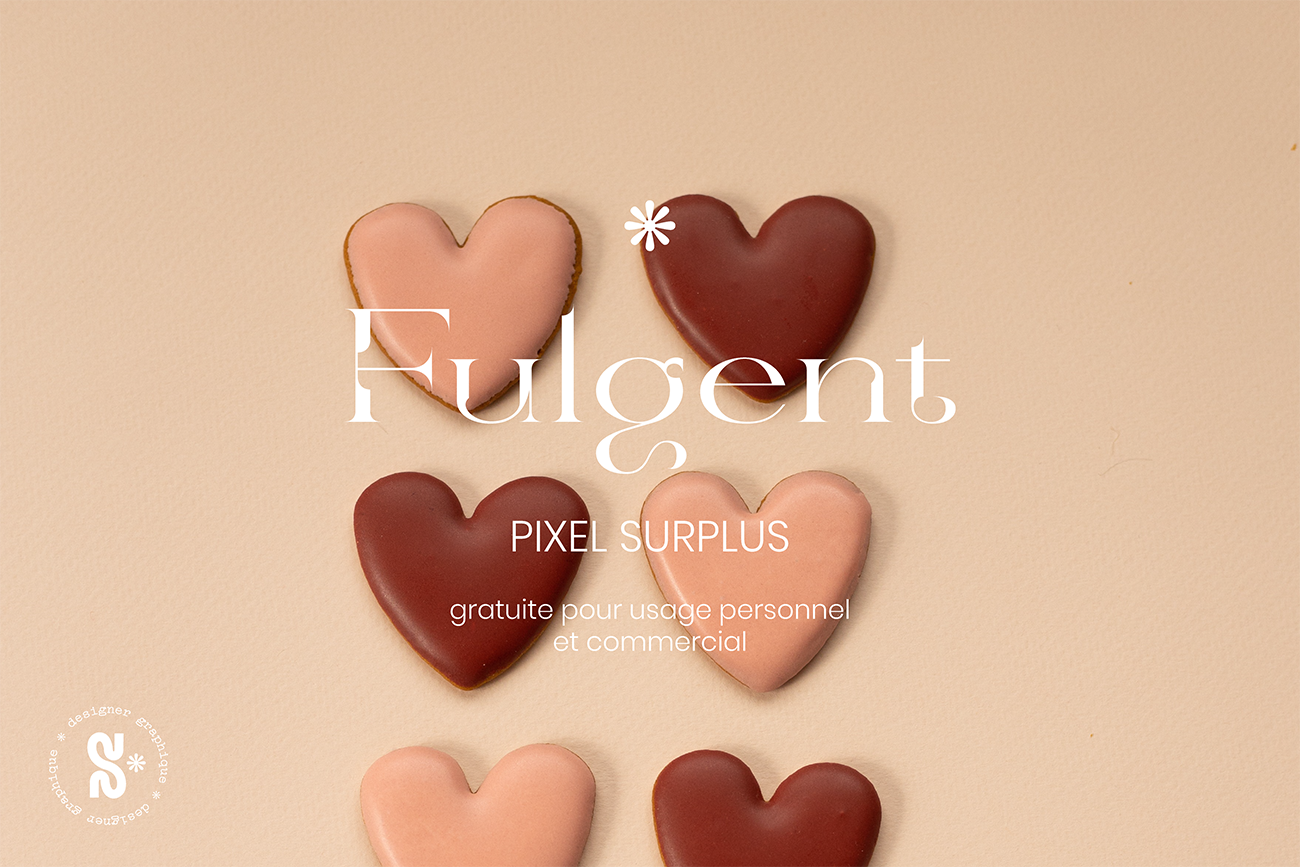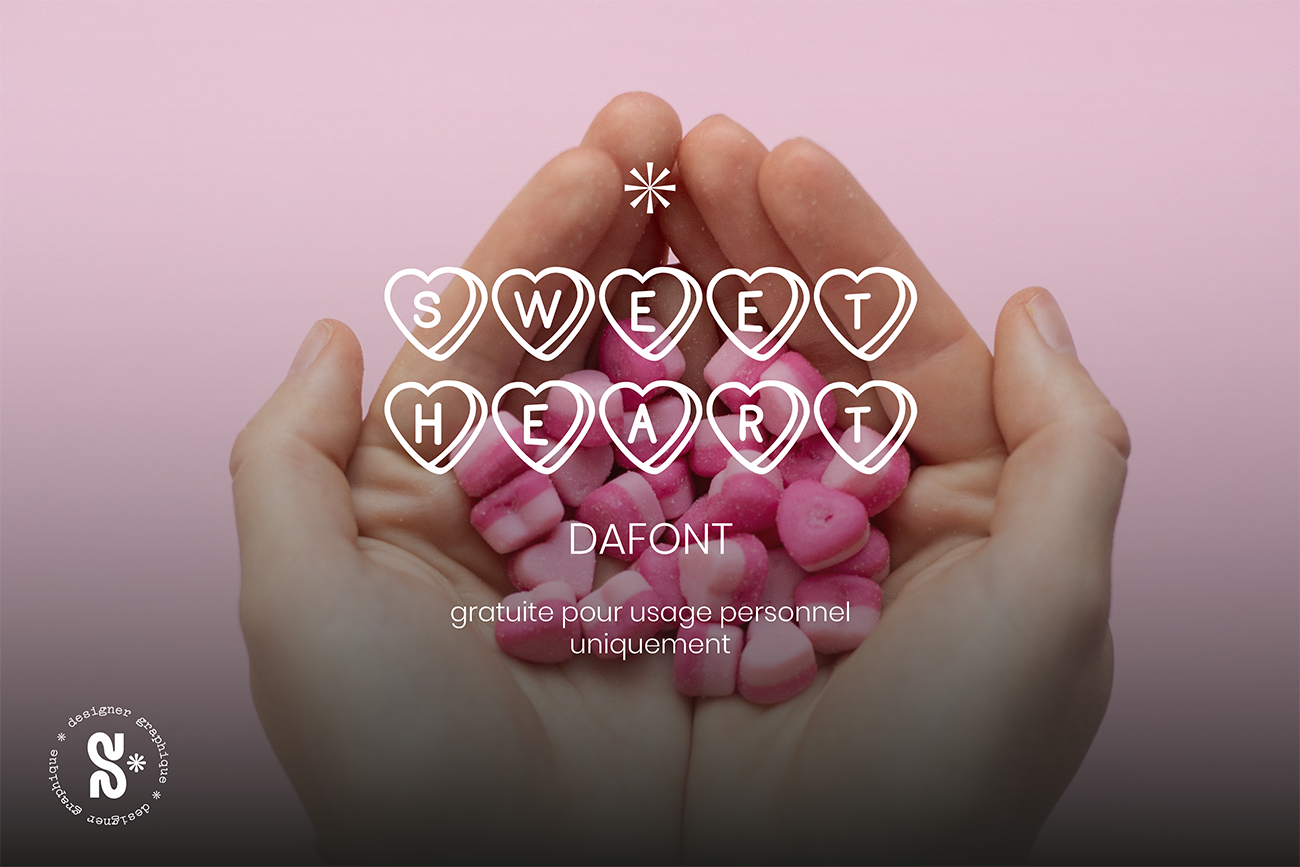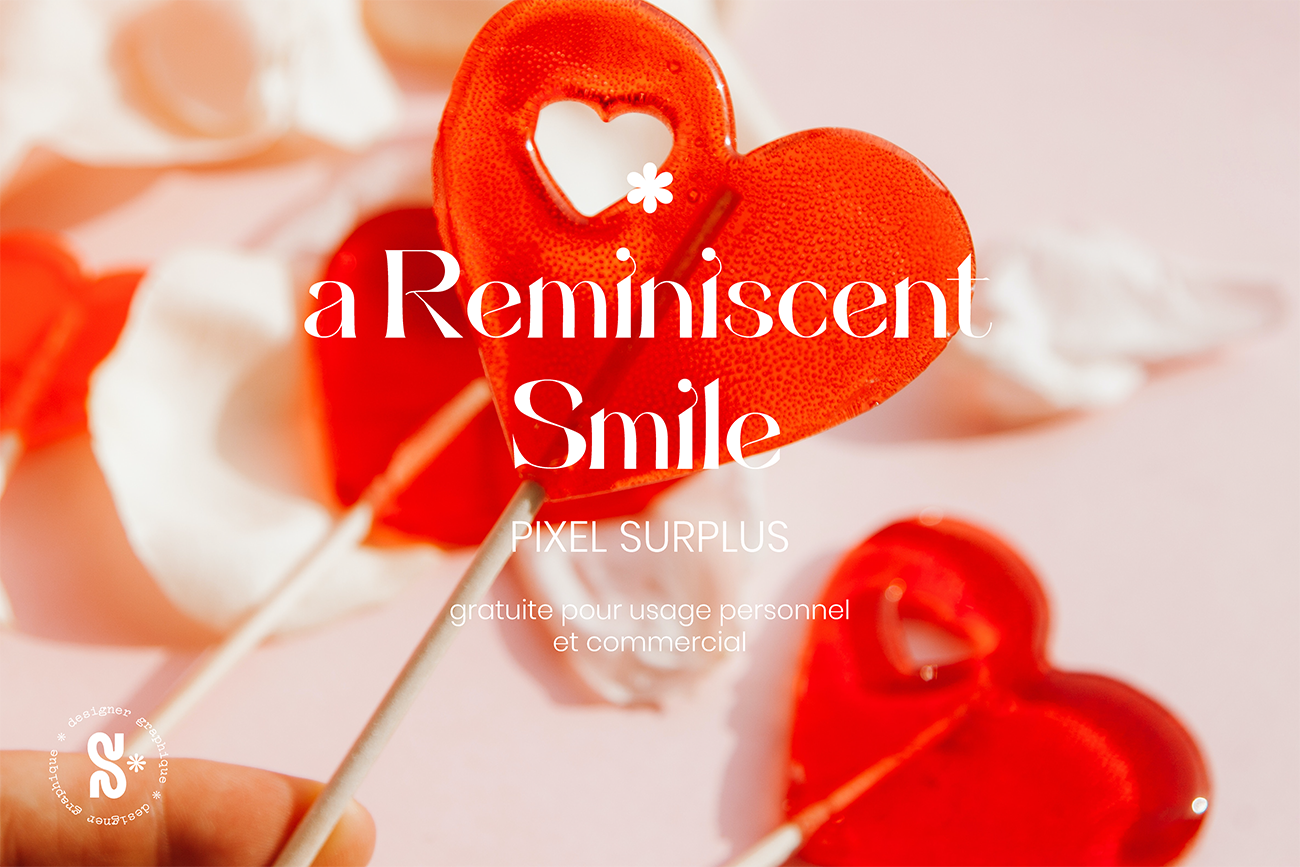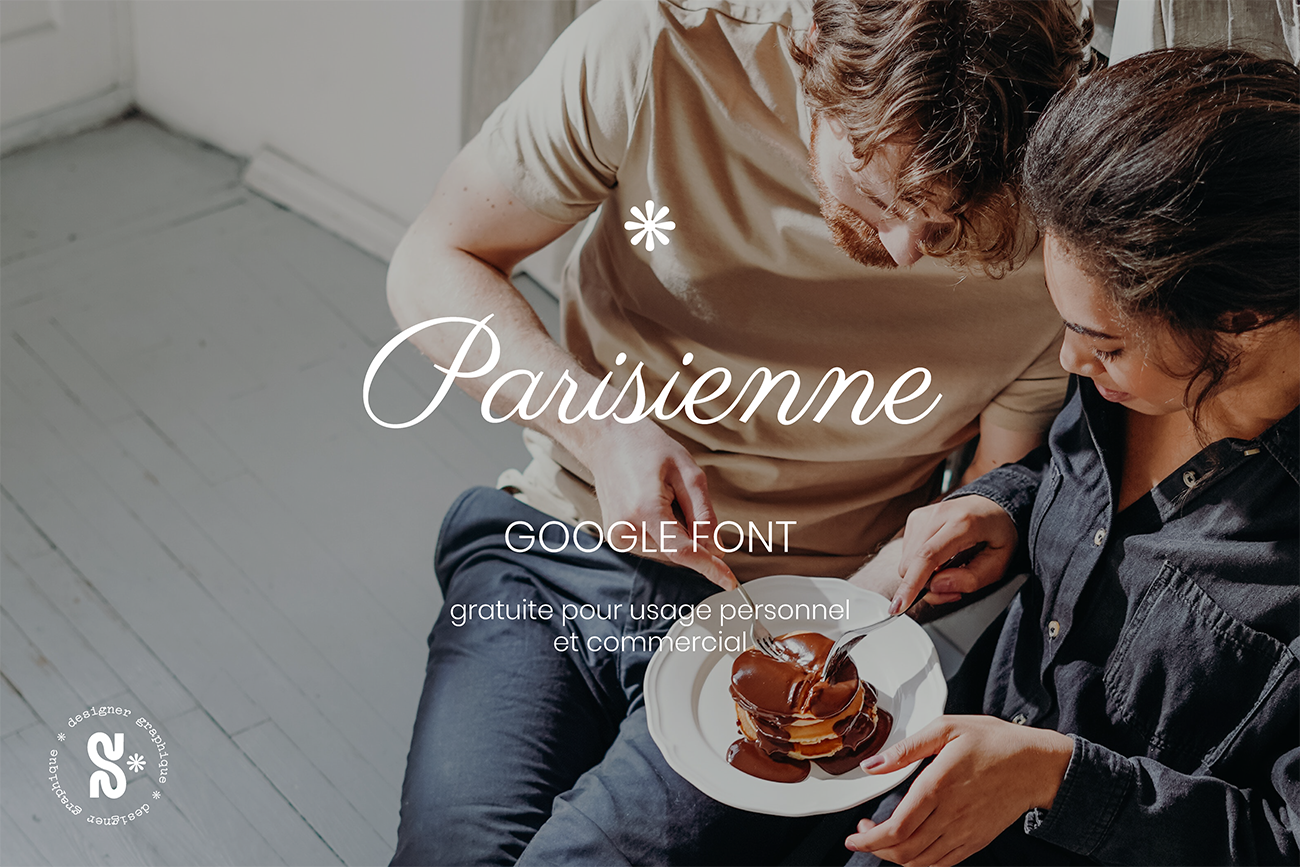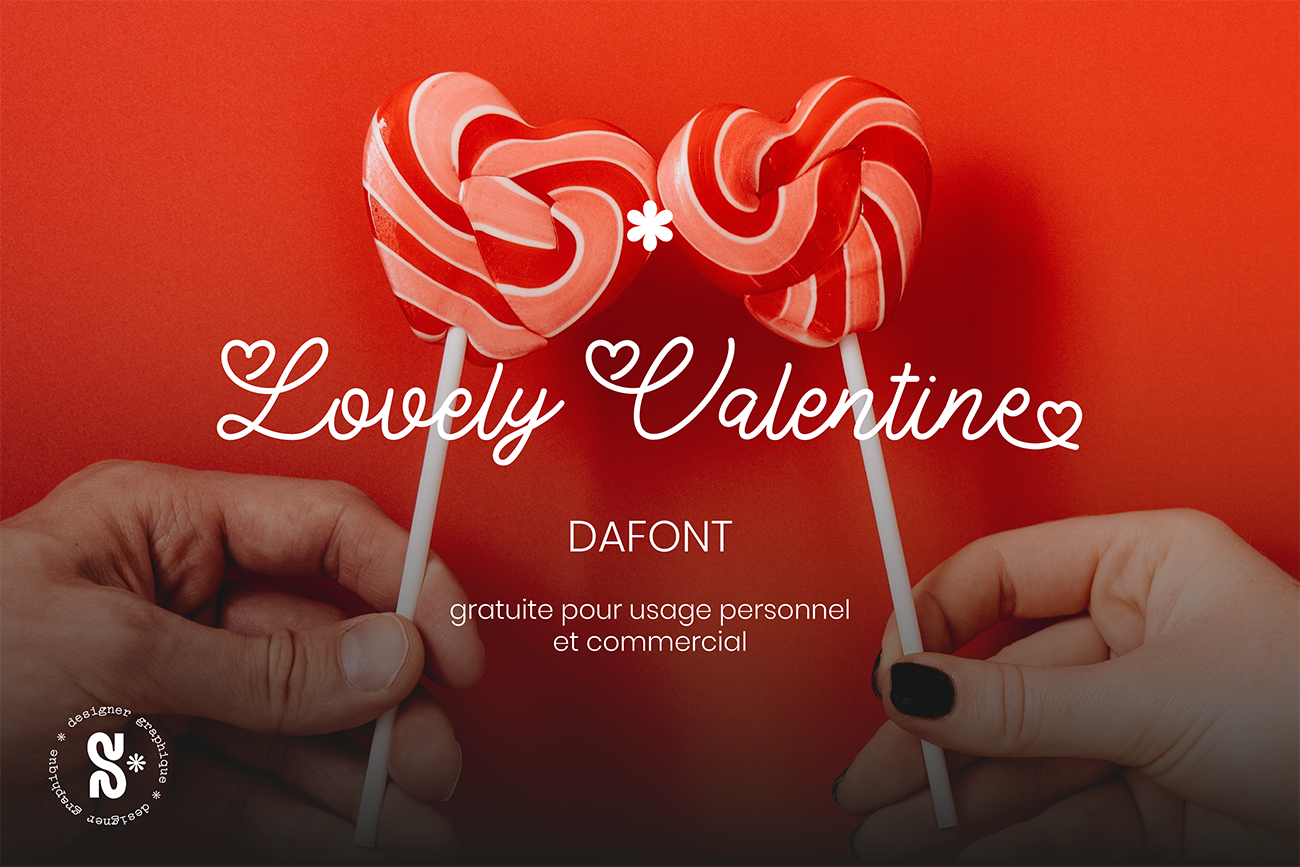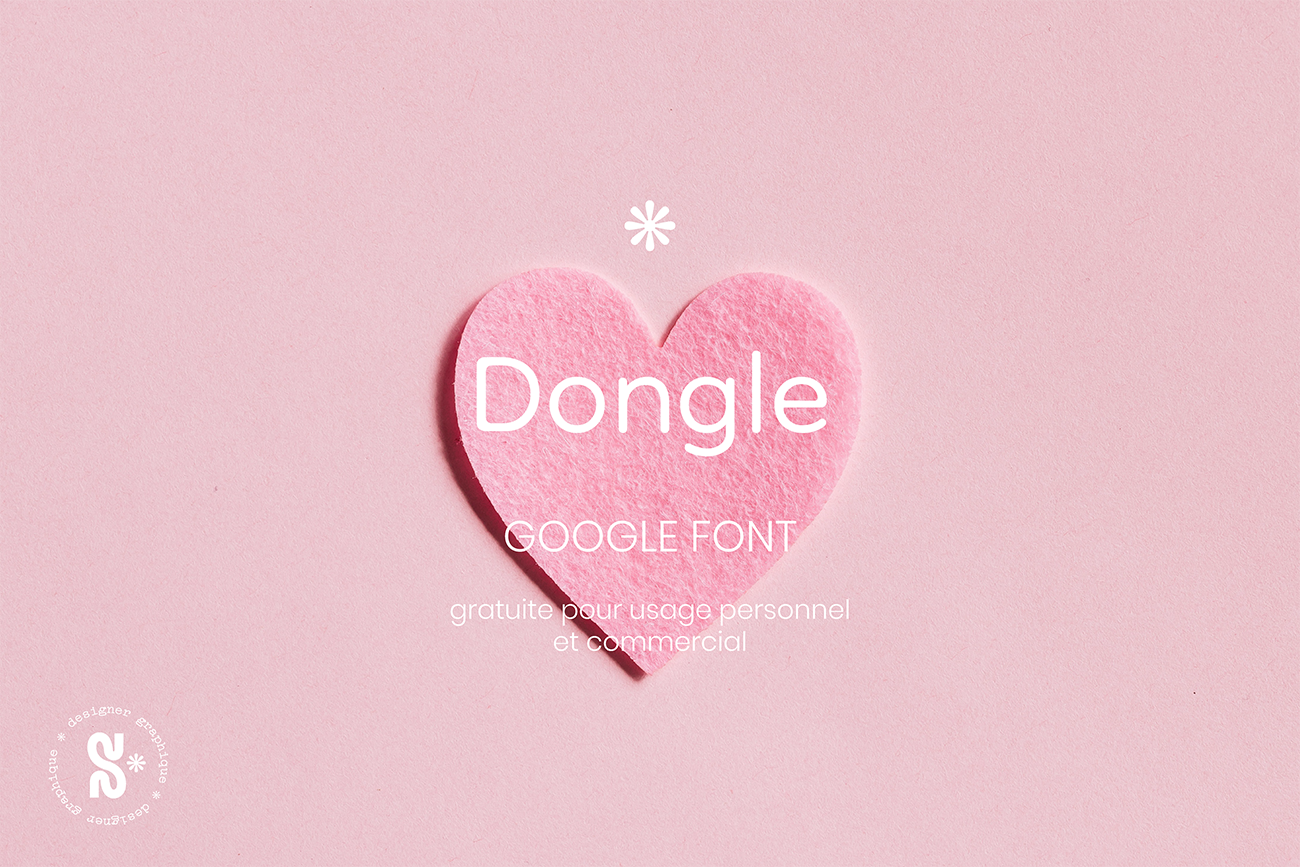
Cela n’a pas du vous échapper, la Saint Valentin approche et la communication s’adapte en conséquence ! Mais qu’en est-il de votre propre communication à cette période ? Pas facile de se démarquer parmi toutes les publications sur notre ami Valentin. Dans ce studio de graphisme, on adore communiquer sur toutes ces fêtes qui ponctuent l’année ! Je me suis dit que c’était le moment de vous aider à communiquer grâce à une sélection de 10 typographies du love gratuites ! Mais avant ça, faisons le point sur la communication pendant la Saint Valentin.
Une communication de Saint Valentin pour célébrer l’amour
Vous souhaitez surfer sur la vague et en profitez pour avoir de nouveaux contenus à poster ? Je vous en dit un peu plus sur cette fête de l’amour et sur ce que vous pourriez mettre en place pour cette occasion.
La Saint-Valentin : une histoire d’amour (ou presque)
Si pour beaucoup la St -Valentin est une fête commerciale, c’est avant tout une journée censée célébrer l’amour. Son histoire remonte au XIVème siècle et est légèrement plus triviale; direction la Grande-Bretagne. À l’époque, on pensait que les oiseaux choisissaient ce jour pour s’apparier, on a donc décrété que le 14 février serait la fête de l’amour. Avec le temps, les amoureux ont pris pour coutumes de s’échanger des billets doux, des fleurs ou encore des chocolats.
Aujourd’hui, impossible de passer à côté de cette fête annuelle. Elle est omniprésente, et si vous souhaitez communiquer sur le sujet, il est important de vous démarquer ! Publications sur les réseaux sociaux, vidéos, petits mots (en tout bien tout honneur) à vos clients…
Autant de supports qui peuvent vous permettre de vous différencier facilement si vous avez les bons outils. Alors pour lâcher un peu la pression, suivez mes conseils de designer graphique !
Comment communiquer à la Saint Valentin
Alors comment communiquer et surtout QUE communiquer pour la Saint Valentin. Selon votre marque, la communication de St Valentin aura plus ou moins d’importance. Si votre produit est étroitement lié à cette fête (bijoux, fleurs, chocolats, papeterie…) il est important de vous différencier. Mettez en avant l’amour sous une autre facette. Communiquez sur vos événements, vos offres spéciales, etc.
À la Saint Valentin comme à tout autre moment de l’année, il est appréciable de se différencier. Vous pouvez par exemple faire une série de posts avec des couleurs liées à cette fête : le rose, le rouge… tout en gardant les éléments phares de votre charte graphique : typographies, éléments graphiques, etc. À l’inverse, vous pouvez conserver vos couleurs mais utiliser une typographie à part entière pour parler d’amour à vos clients (car ce sont eux votre plus belle histoire d’amour, pas vrai ?).
Et si je ne changeais rien pour ma communication de St-Valentin
Mon conseil le plus important ? Lâcher prise. Vous ne souhaitez pas communiquer différemment lors de la Saint Valentin ? Vous pensez que cela n’est pas pertinent auprès de votre cible ? Alors ne changez rien ! Il est important de ne pas céder à la pression du moment et de s’écouter.
Les fêtes sont une belle occasion de communiquer certes, mais il est important de le faire de la bonne manière et en accord avec les valeurs et envies de votre projet. Comme je le dis souvent; la qualité avant la quantité.
Mon cadeau de Saint Valentin
En cette période où l’on s’échange des mots doux, je vous partage 10 typographies parfaites pour votre communication de Saint Valentin. Entre tradition et audace, ces polices donneront à vos créations une touche unique afin de vous démarquer. Et petit plus : elles sont gratuites !
Prêtes et prêts à découvrir cette sélection ? Ouvrez grand votre coeur et laissez-vous guider !
1 – Une communication de Saint Valentin unique avec Fulgent
Fulgent est une typographie gratuite parfaite pour une communication de Saint Valentin différenciante. Originale par ses lettres aux futs coupés, elle apporte un côté rêveur pour une communication délicate. À découvrir sur Pixel Surplus
2 – Le fun de la typographie Sweet Heart
Sweet Heart est la typographie de Saint Valentin version US par excellence : fun et gourmande. Elle est inspirée de le marque de bonbon américains du même nom en forme de coeur. Un clin d’oeil que j’adore ! À télécharger gratuitement sur Dafont
3 – La délicatesse de la police A Reminiscent Smile
La typographie A Reminiscent Smile est délicate et offre quelques courbes évoquant la calligraphie. Une font qui donne un côté luxueux à votre communication de St-Valentin ! À retrouver gratuitement sur Pixel Surplus
4 – La typographie calligraphique chic : Parisienne
Si je ne suis pas une grande amoureuse des typographies scripts, je dois avouer que la font Parisienne me fait de l’oeil. Imitant une écriture calligraphique humble, elle est équilibrée et parfaite pour un côté « lettre à l’amour ». À découvrir sur Google Font
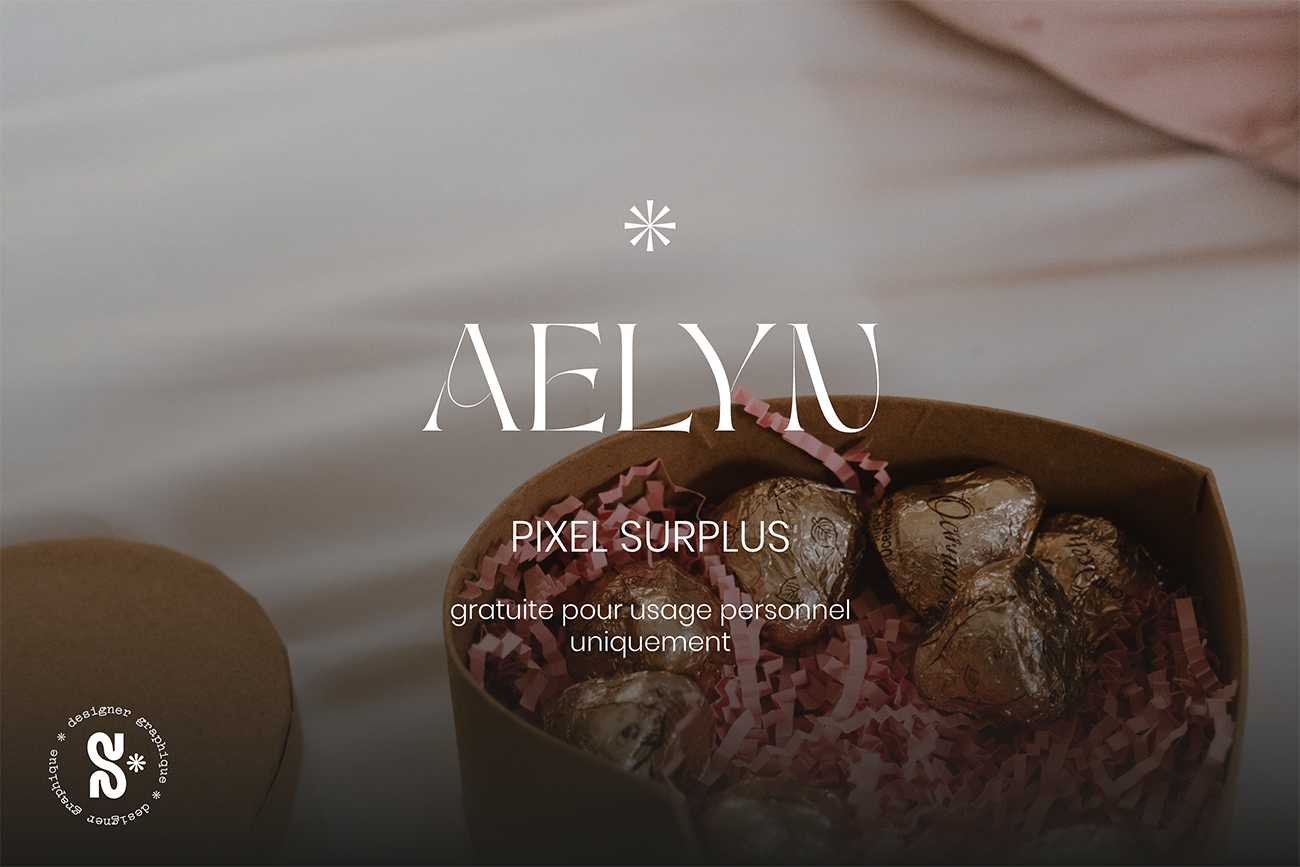
5 – L’équilibre entre élégance et modernité avec la police Aelyn
C’est un de mes coups de coeur de la sélection, la police Aelyn marie à merveille l’élégance d’une typographie Sérif tout en lui apportant des courbes rondes. Ses traverses atypiques en font selon moi une typographie différenciante et unique ! À télécharger gratuitement sur Pixel Surplus
6 – La typographie Lovely Valentine pour une communication 100% love
Lovely Valentine est une typographie faite pour la St Valentin. Ronde, douce et juste ce qu’il faut de variation pour la rendre dynamique. Les petits coeurs sont le plus 100% Saint Valentin. À retrouver gratuitement sur Dafont
7 – La rondeur pleine d’amour de Dongle
Vous souhaitez apporter une touche minimaliste à votre communication de St-Valentin ? Rien de mieux que d’utiliser la typographie Dongle. Simple mais ronde, elle apporte de la proximité à votre communication. À découvrir gratuitement sur Google Font
8 – Une lettre écrite avec la typographie I Love Glitter
Vous souhaitez écrire une lettre d’amour à vos clients ? I love glitter est la typographique qu’il vous faut. Une police manuscrite lisible et équilibré et parfois ponctuée d’amour ! À retrouver gratuitement sur Font Space
9 – La finesse de la police Pencerio
La typographie a été créée pour donner un twist contemporain aux typographies scripts plus traditionnelles. Sa finesse promet une communication douce et délicate. À découvrir gratuitement sur FontShare
10 – Une communication de Saint Valentin tout en proximité avec South Town
Amoureux de la typographie faite main, la South Town est faite pour vous ! Une écriture qui peut tout à fait s’accorder avec une communication proche de vos clients. À retrouver gratuitement sur Pixel Surplus
Retrouvez cette sélection en format vidéo sur mon compte instagram !
Studio Hélioscope : spécialiste de la typographie pour votre communication
Vous me découvrez en lisant cet article ? Je suis Salomé, une designer graphique freelance lyonnaise. Mon envie ? Faire rayonner les entrepreneurs et leur projet en apportant du sens à leur communication visuelle. Et la typographie, c’est selon moi l’un des atouts majeurs de cette communication. Je m’efforce de trouver la police idéale pour chacun de mes clients. Selon ses goûts, ses besoins et ses attentes, je sélectionne et modifie une typographie pour qu’il ou elle puisse se l’approprier. Curieux d’en voir plus en matière de typographie ? Je vous invite à jeter un oeil aux différents projets que j’ai pu mener.